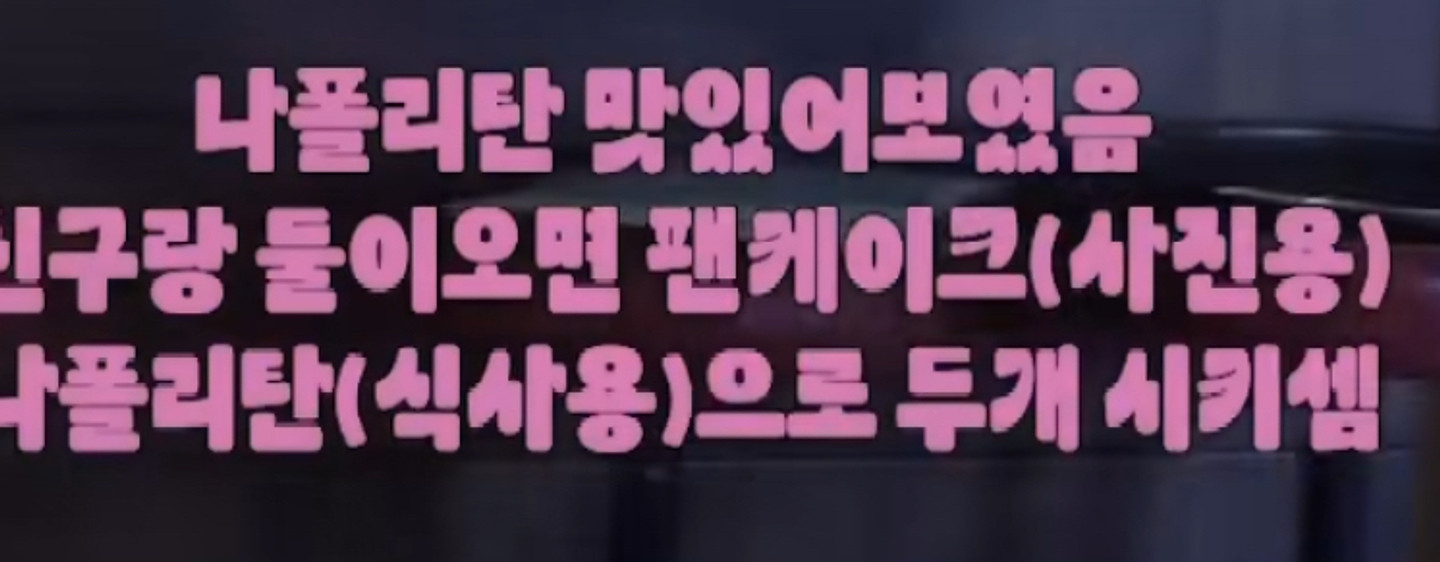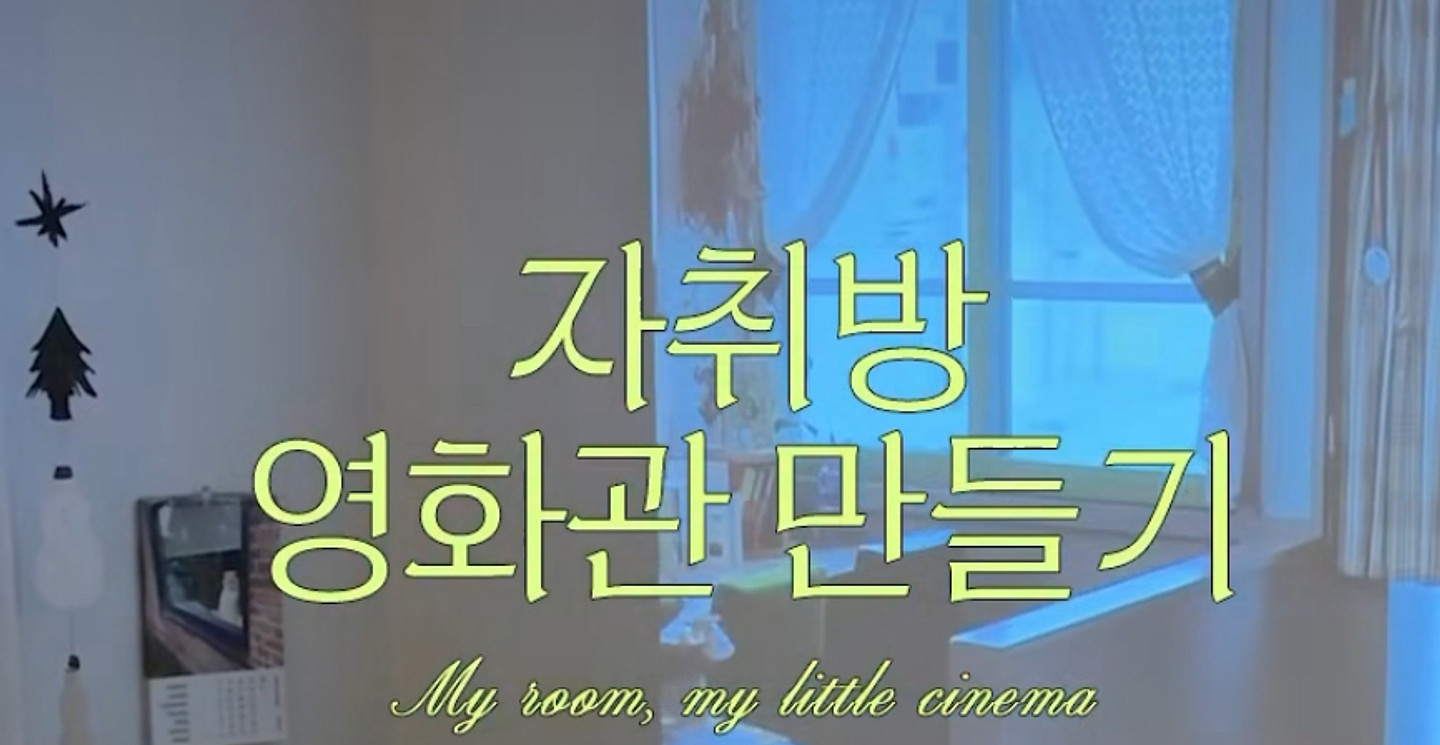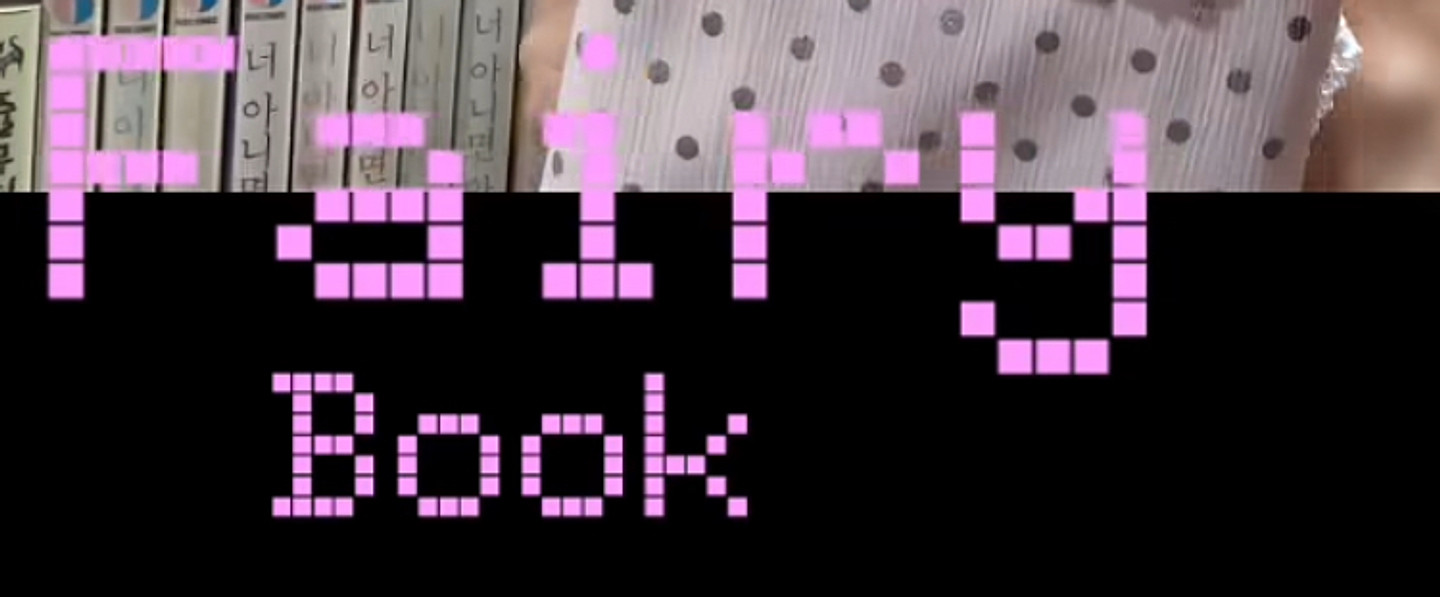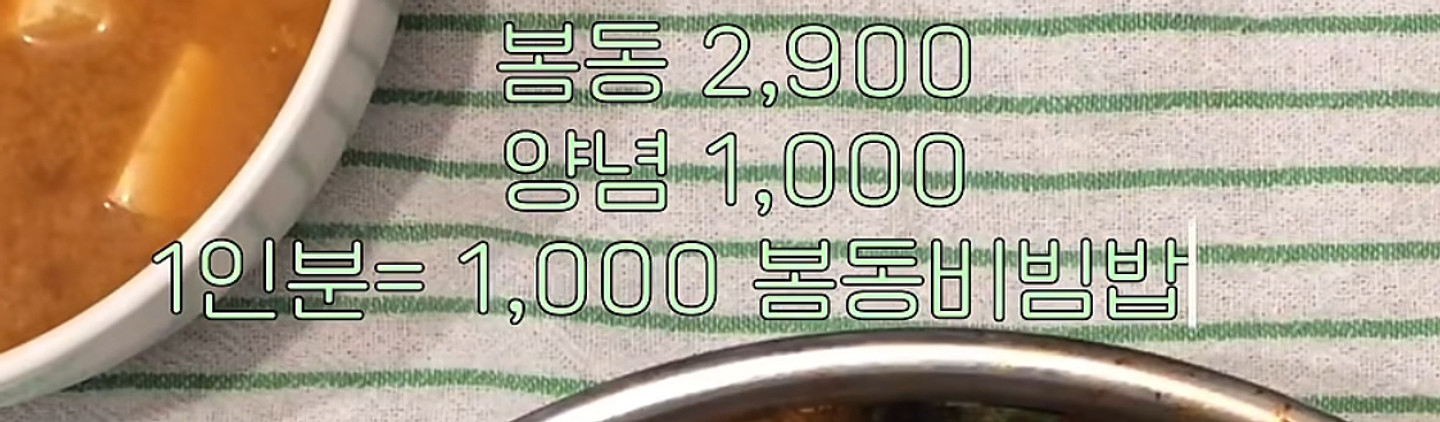
자막 폰트 궁금해용
답변 잘 받았습니다. 대댓글쓰는곳이없는거같아서요 캡쳐한뒤 다시 말씀이어서 드립니다 .,ㅎㅎ추천해주신 Soul 커피브레이크, Soul 율곡, Soul 데스페라도도 확인해봤는데 제가 원하는 것보다 획이 조금 가늘고, 구독형이라 장기간 반복해서 사용하기에는 부담스럽더라고요. 제가 찾는 폰트는 글자가 굵고 통통하면서도 손으로 쓴 것처럼 불규칙하고, 붓의 거친 결이나 긁히고 벗겨진 느낌이 있는 한글 붓글씨입니다. 구독형보다는 상업용 유튜브 썸네일에 사용할 수 있는 무료폰트나, 한 번 구매하면 계속 사용할 수 있는 유료폰트가 있으면 여러 개 추천 부탁드립니다. 현재 눈누에서 찾아본 폰트 중에는 그리운 경찰감성체, 정선아리랑체, 눈누마켓의 HCL 둥글납작펜을 후보로 생각하고 있습니다. 이 중 한 가지를 사용해서 외주 제작자에게 After Effects 작업을 맡기고, 완성된 MOGRT를 받아 제가 Premiere Pro에서 제목만 바꿔가며 유튜브 썸네일에 계속 사용하고 싶은데요. 이런 경우 각 폰트마다 제가 구매하거나 다운로드한 폰트를 외주 제작자가 작업에 사용할 수 있는지, 아니면 제작자도 별도의 라이선스나 구매가 필요한지 궁금합니다. 무료폰트라면 저와 제작자가 각자 공식 페이지에서 다운로드해 설치하면 되는지도 알고 싶습니다. 또한 완성된 MOGRT에 폰트 파일 자체는 포함하지 않고, 제가 제 컴퓨터에 폰트를 따로 설치한 상태에서 문구만 반복해서 바꿔 사용하는 방식이라면 상업적으로 계속 사용해도 괜찮은지도 확인 부탁드립니다.